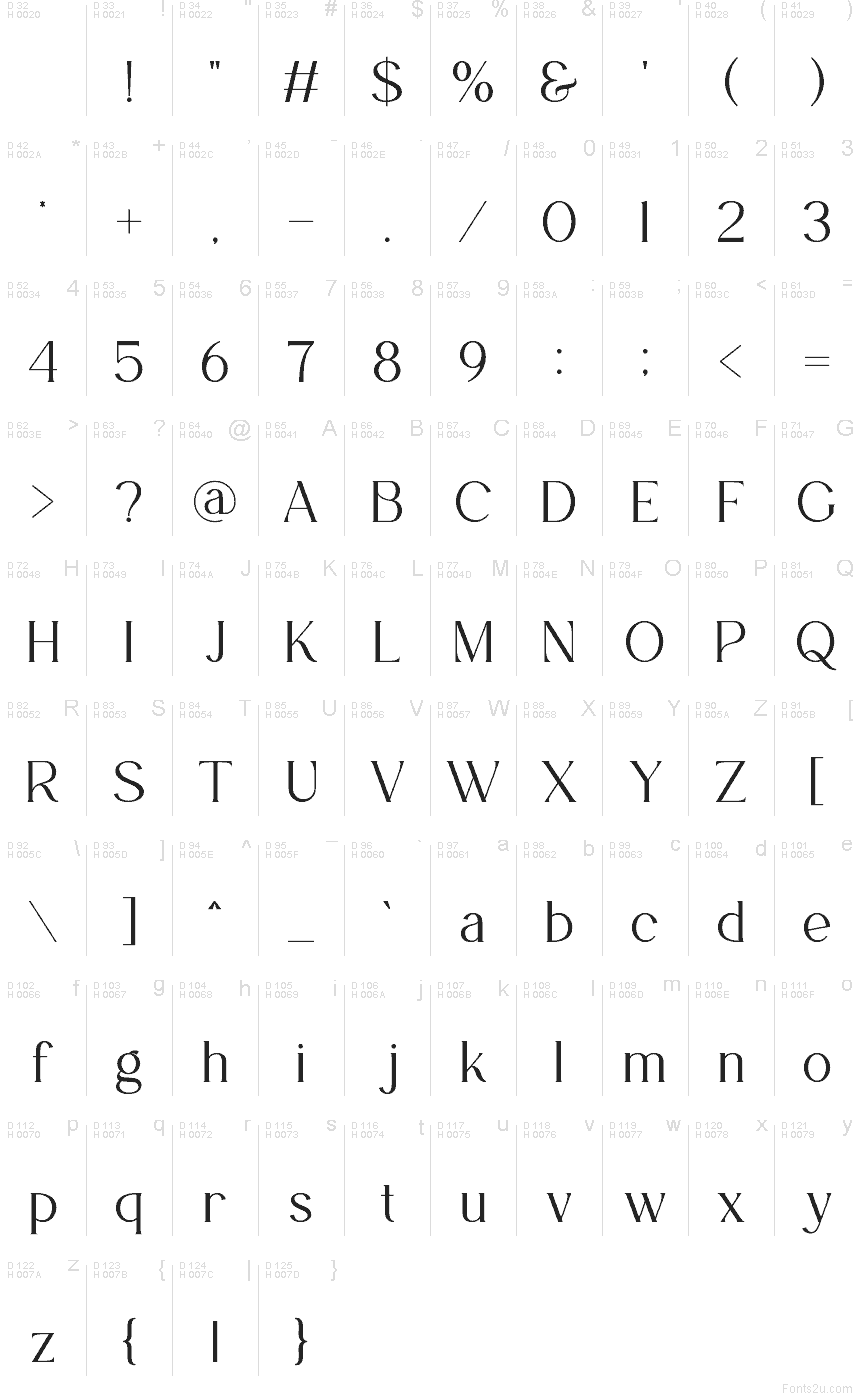
Obhiros Regular
Il carattere Obhiros di ErmediaStudio è un serif gratuito che sembra disegnato con un pennino finemente inchiostrato: tratti sottili e slanciati incontrano grazie nette e affilate. Le forme delle lettere sono alte e ariose, con occhielli rotondi quasi fluidi accanto a verticali pulitissime, per un effetto di eleganza discreta e lusso misurato. C’è una tensione sottile tra morbidezza e incisività che cattura subito lo sguardo e fa apparire Obhiros come una scelta di gusto, mai banale.
Con Obhiros, titoli e nomi acquistano un tono boutique ed editoriale perfetto per loghi, branding beauty o fashion, copertine di riviste, sovraccoperte, packaging e inviti di fascia alta. Questo font gratuito rende al meglio in corpi più grandi, dove i suoi dettagli raffinati possono emergere davvero. Per un abbinamento semplice e affidabile, usa Obhiros nei titoli e affiancalo a un sans serif pulito per i testi di supporto, così l’impaginazione resterà contemporanea e ben equilibrata.